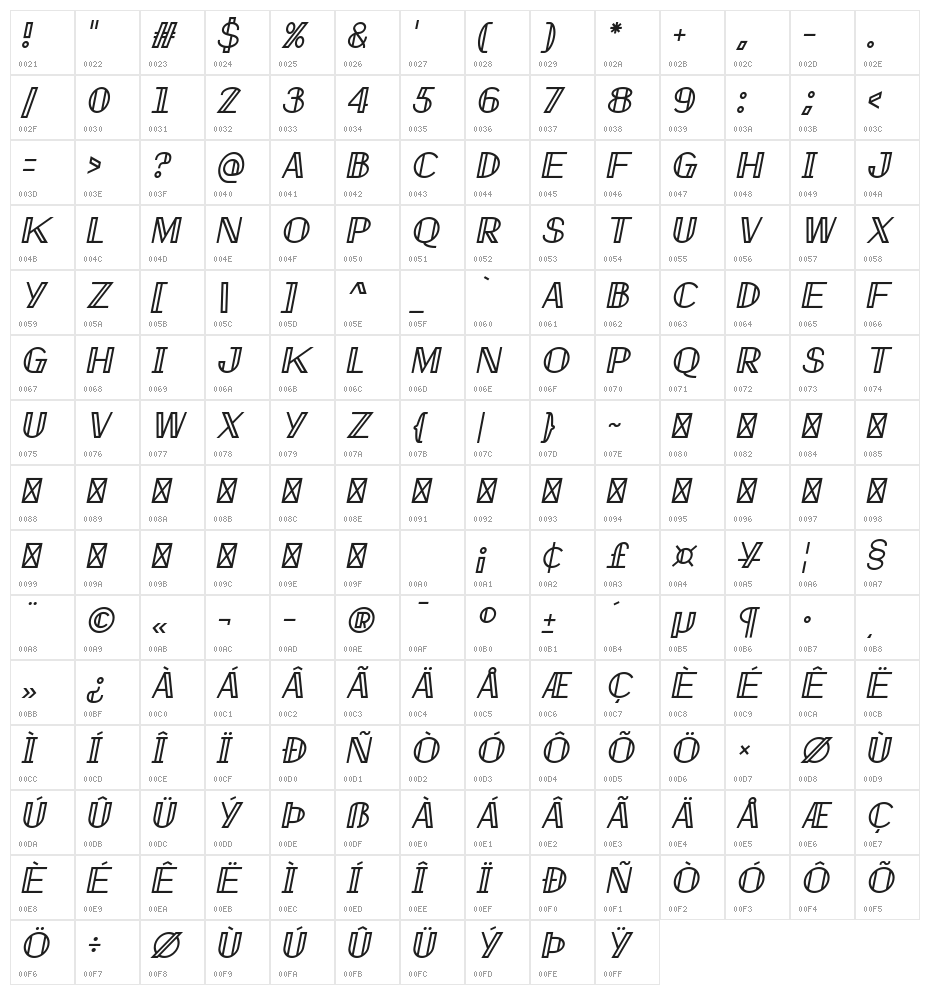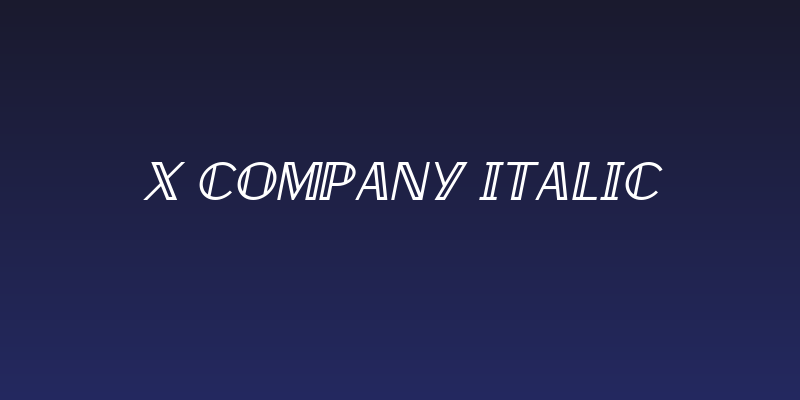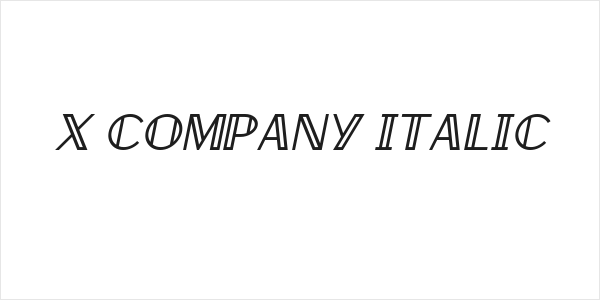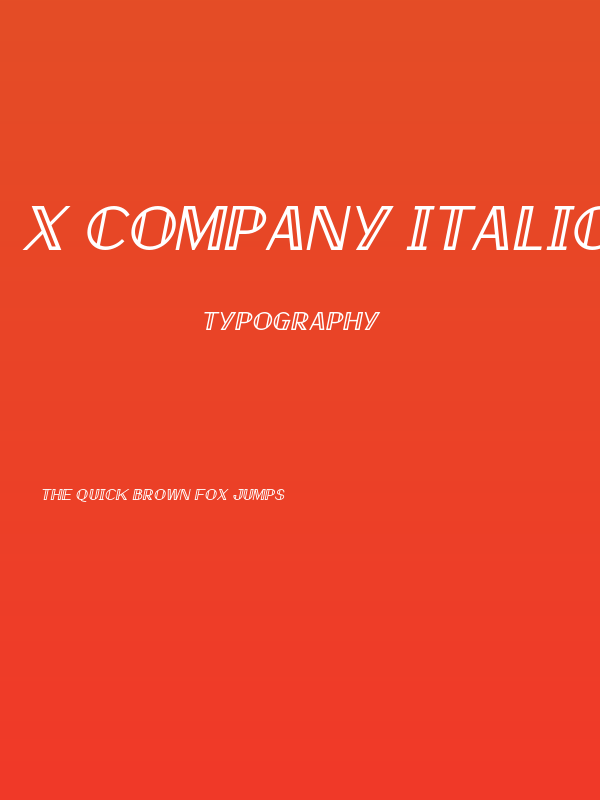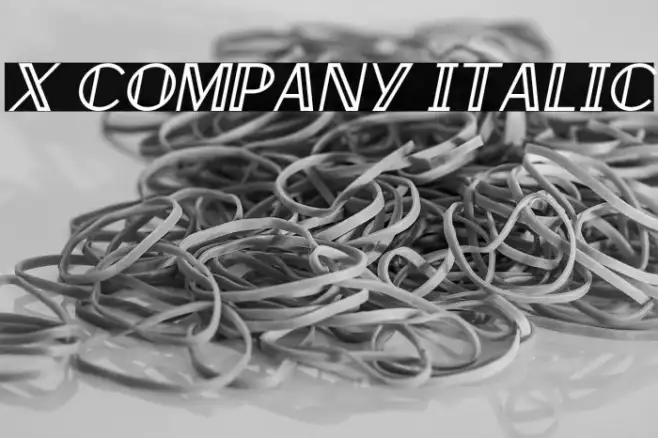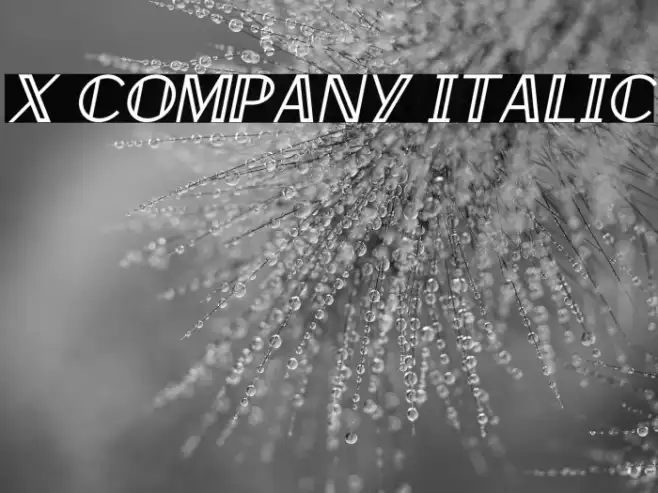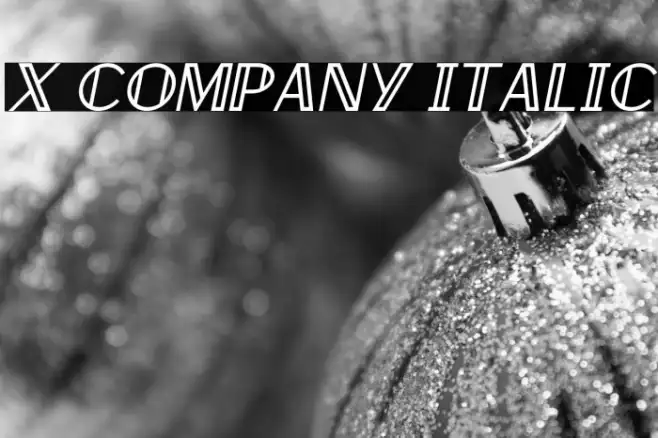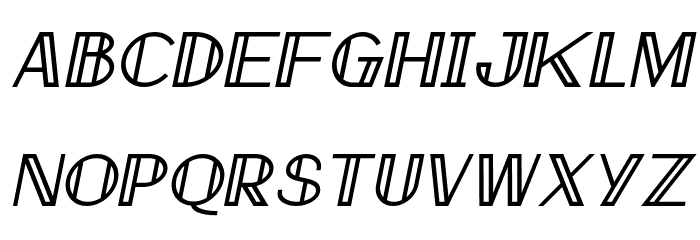
X Company Italic Font
| Anwendungsfall | Headlines, Logos, Branding |
| Vorgeschlagene Projekte | Ideal for branding, advertising, and editorial design projects that require a modern and energetic feel. |